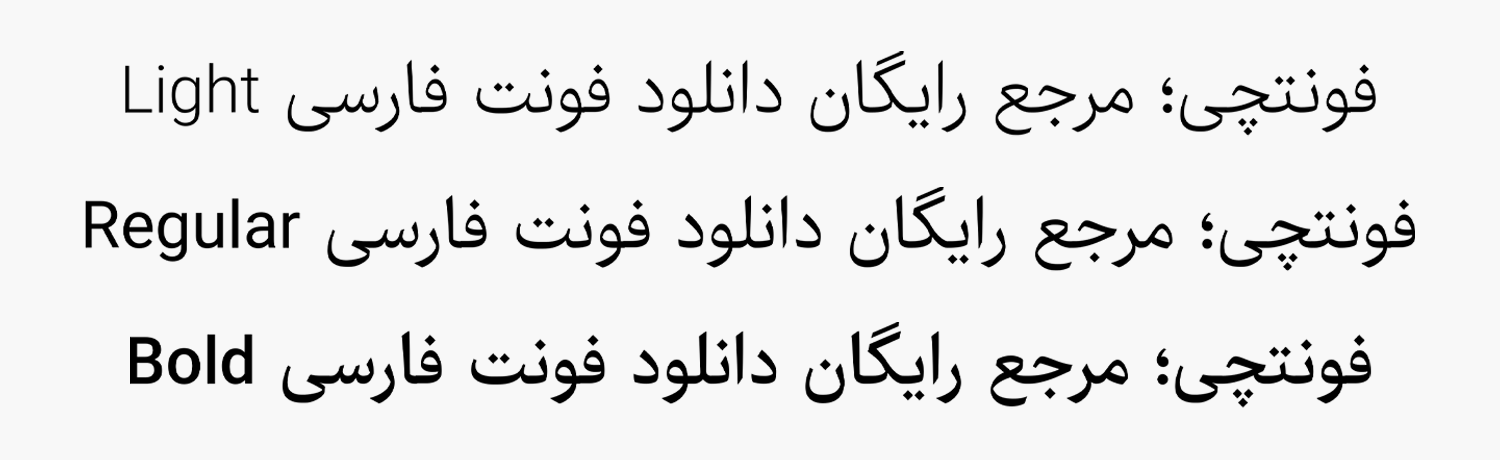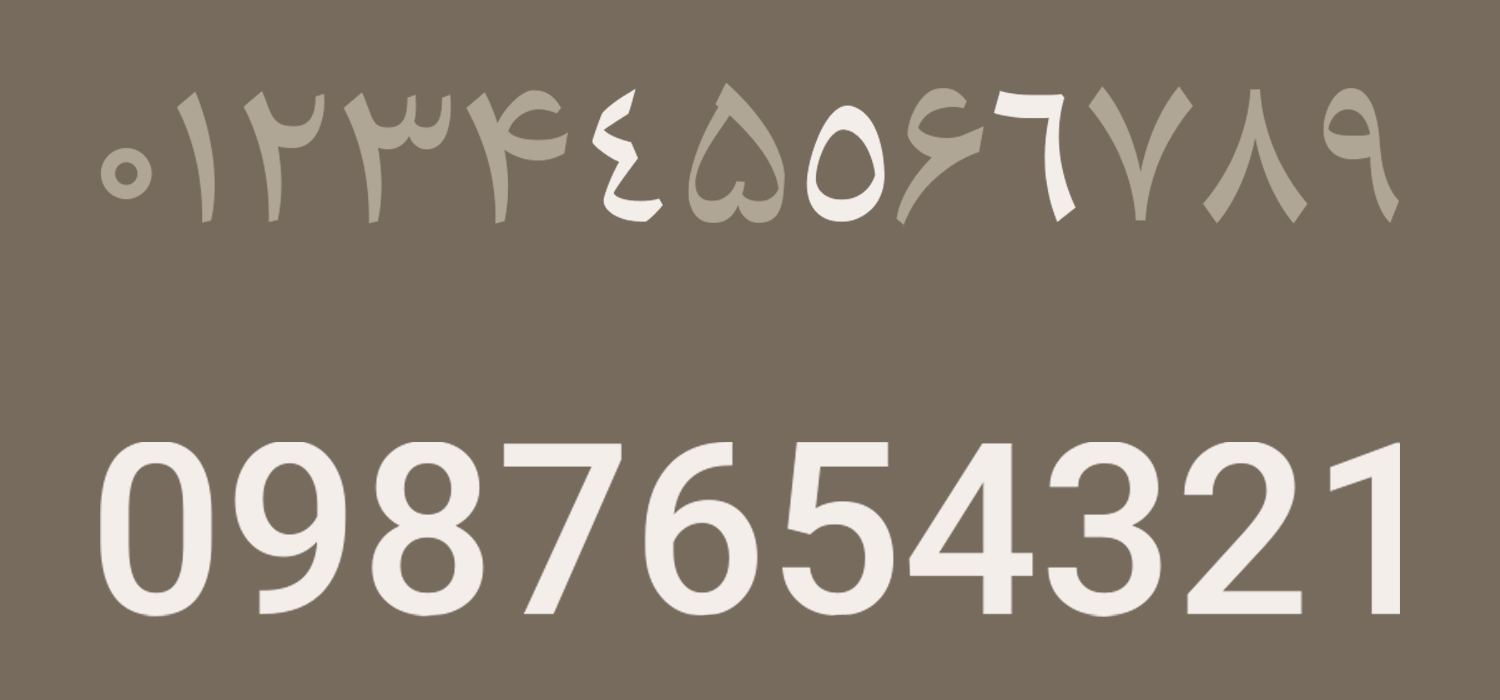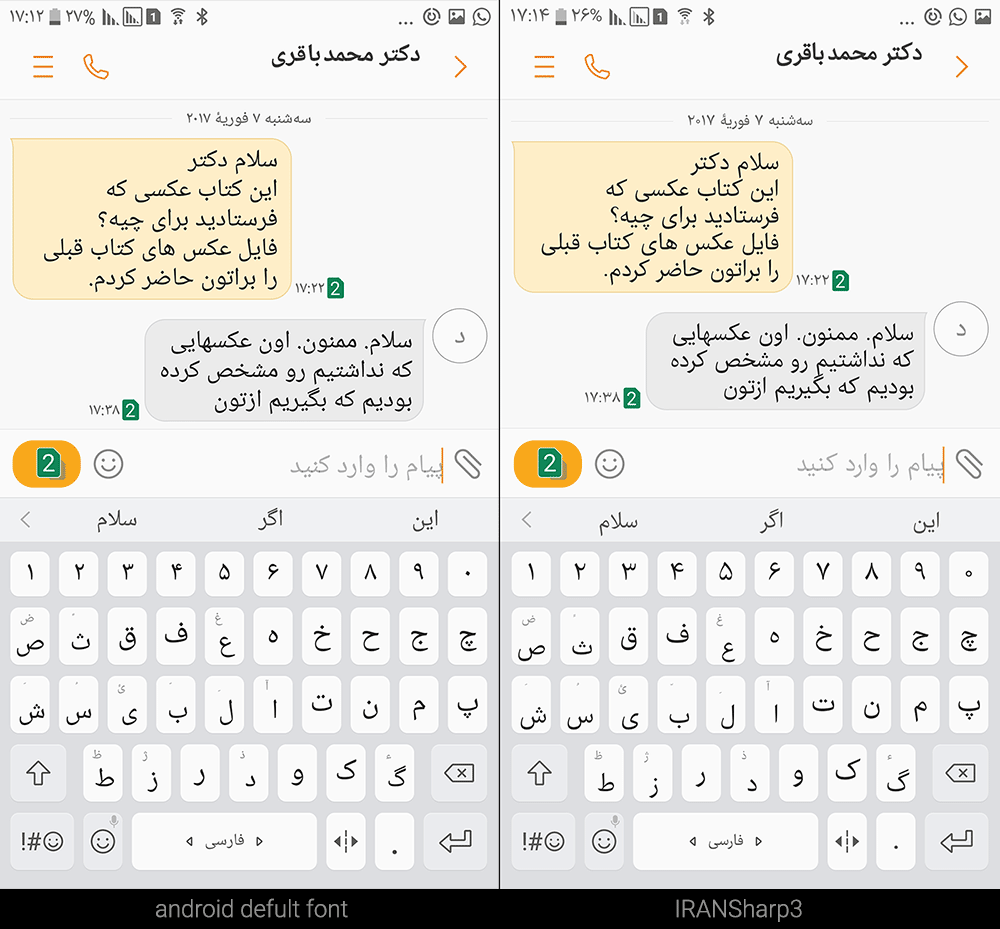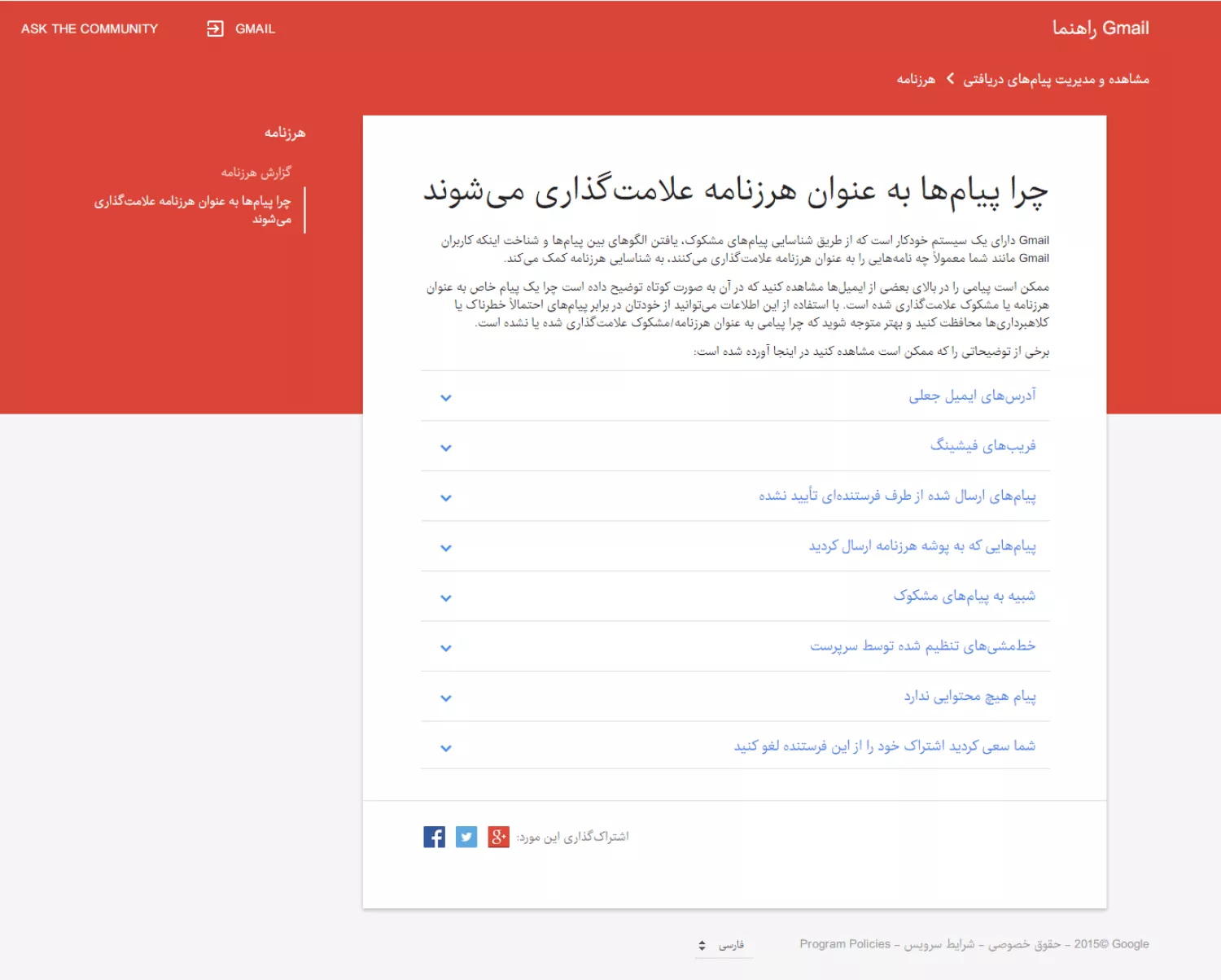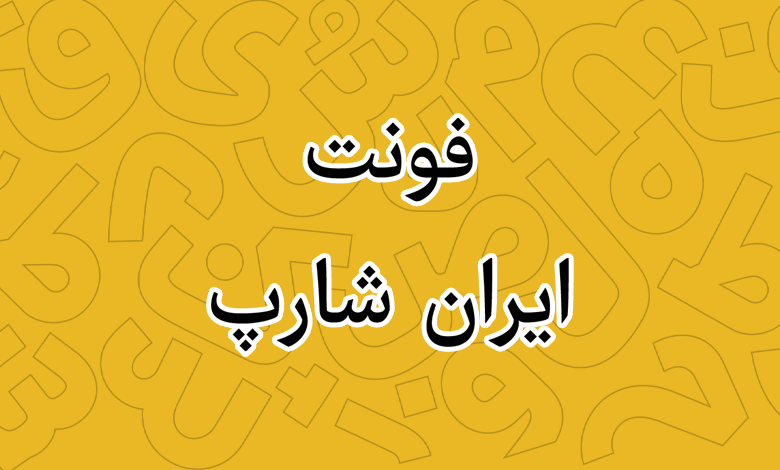
فونت ایران شارپ (iran-sharp)
فونت ایران شارپ (به انگلیسی: iran-sharp) از دیگر قلمهای فارسی مناسب برای متنهای طولانی است که بیشترین کاربرد را در صنعت مطبوعات و چاپ دارد. اما با توجه به اهمیت استفاده از این قلم در چنین صنعتی، برای استفاده در فضای دیجیتال بهویژه وبسایت و اپلیکیشن نیز انتخابی عالی بهشمار میآید.
این قلم که بر اساس خط نسخ طراحی شده، طراحی نزدیکی با بهترین فونت های فارسی معاصر نظیر زر، نازنین، میترا، لوتوس و بدر دارد که توسط مسلم ابراهیمی طراحی شده است. این قلم را میتوان نسخه اولیه برای قلمی در نظر گرفت که در نهایت پس از سالها نسخه پخته شده آن با نام فونت فرهنگ توسط همین طراح ساخته و در دسترس عموم قرار گرفت.
در ادامه این نوشته از سایت فونتچی به نقد و بررسی کامل قلم ایران شارپ خواهیم پرداخت؛ فونتی در قالب سه وزن که در ۵ فرمت فایل مختلف در دسترس بوده و با توجه به تنوع و ساختاری که از نظر نسخه مناسب برای اعداد فارسی و بدون حروف انگلیسی دارد، میتوان از آن برای متنهای بلند بهترین بهره را برد.
با اینکه قلمهایی نظیر زر، میترا، نازنین و… بیش از نیم قرن است که مورد استفاده قرار میگیرند؛ اما با ظهور سبک دیجیتال و فاصله گرفتن دنیای آن از حروفچینی، اکنون مشکلات و ایرادهای مختلفی را داشتند که در سالهای گذشته احساس به وجود قلمی در همان سبک کاملا وجود داشت.
با اینکه در این سالها افراد مختلفی سعی داشتند که قلمهای مورد نظر را اصلاح کرده و تغییراتی در آن ایجاد کنند که متناسب با نیاز فعلی باشد؛ اما این کار به سرانجام نرسید تا اینکه در نهایت قلم ایران شارپ متولد شد.
سبک طراحی و وزن فونت ایران شارپ
استفاده از فونت ایران شارپ برای افرادی که وابستگی زیادی به سبک فونتهای زر، نازنین، میترا، لوتوس و بدر داشتند مناسب است تا قلمی عاری از اشکالات نرمافزاری را در اختیار داشته باشند.
فونت ایران شارپ در طول این سالها بارها بهروزرسانی شده و ضمن رفع ایرادات جزئی که در آن وجود داشته تغییراتی نیز بر روی آن اعمال شده است که در نهایت به شکل امروزی آن را مشاهده میکنید.
این قلم مشابه سایر تایپفیسهای فارسی از سه وزن نازک (Light)، معمولی (Regular) و ضخیم (Bold) پشتیبانی میکند که تمامی بخشهای حروف در هر سه وزن به نسبت تغییراتی وزنی به خود گرفته و هر چه وزن بیشتر میشود، فونت از حالت استخوانی خارج شده و ظاهری نرم و شارپتر بهخود میگیرد.
پشتیبانی از زبان فارسی و عربی
اگر به دنبال بهترین فونت فارسی هستید، ایران شارپ را میتوان یکی از این قلمها دستهبندی کرد؛ با اینکه شاید این قلم را زیاد در فضای دیجیتال ندیده باشید، اما در فضای مطبوعات و صنعت چاپ همچون روزنامه و کتابها بهوفور از این قلم استفاده میشود.
این قلم علاوه بر زبان فارسی، از زبان عربی نیز پشتیبانی میکند. این زبان به لطف اینکه بر پایه رسم خط فارسی است در این قلم قرار داده شده است که علاوه بر پشتیبانی از حروف و گلیفهای استاندارد فارسی، از حروف عربی نیز پشتیبانی میکند.
برای نمونه میتوان به حروف «ک، ی، ه، ؤ، ئ» اشاره کرد که در زبان فارسی مورد استفاده قرار نمیگیرند؛ در حالی که زبان عربی مملو از این ساختارها میباشد.
پشتیبانی این فونت از زبان انگلیسی نیز فراهم است، اما با این تفاوت که از فونت پیشفرضی که درون گلیفهای آن جاسازی شده استفاده میشود که طراحی بسیار نزدیکی بر مبنای نسخه فارسی و عربی قلم دارد.
ویژگی دیگر قلم ایران شارپ، پشتیبانی استاندارد حروف در زبان فارسی و عربی است. در این قلم اعداد «۴۵۶» عربی که نسبت به اعداد فارسی «۴۵۶» ظاهر متفاوتی دارند پیاده شده است. کافی است صفحه کلید شما روی زبان عربی قرار داشته باشد تا بتوانید از این اعداد استفاده کنید.
اما علاوه بر این نسخه، در درون بسته دانلود فونت ایران شارپ پوشه مخصوص اعداد فارسی هک شده نیز قرار دارد. این گروه از فایلهای فونت که به اختصار با پیشوند FD که مخفف Farsi Digits است نامگذاری شدهاند، فاقد اعداد لاتین بوده و در عوض وقتی اعداد را بر مبنای زبان انگلیسی یا با استفاده از بخش ماشین حساب صفحه کلید تایپ کنید، فارسی تایپ خواهند شد.
مناسب فونت موبایل و مطبوعات
همانطور که اشاره شد فونت ایران شارپ از نظر خوانایی انتخابی عالی بهشمار میرود؛ چرا که یک فونت کاملا شارپ محسوب میشود که تمامی بخشهای حروف نظیر دندانهها، منحنیها و خطوط قائم به شکلی درنظر گرفته شده که موجب خوانش راحت متنون طولانی میشود.
لذا از این فونت میتوانید به عنوان فونت پیشفرض گوشی موبایل نیز استفاده کنید که در تصویر زیر نمونه نصب شده آن را بر روی گوشی سامسونگ مشاهده میکنید.
از دیگر کاربردهای این قلم میتوان به استفاده در فضای مطبوعات و صنعت چاپ اشاره کرد که بیشتر برای چاپ روزنامه، مجلات، کتاب و حتی طراحی جلد کتب استفاده میشود.
در تصویر بالا نمونه این قلم را برای صفحه راهنمای جیمیل مشاهده میکنید که مربوط به نسخههای قدیمی بوده است. همانطور که میبنید از وزنهای مختلف آن در این صفحه استفاده شده ایت که تمامی متون خوانایی لازم را در دستگاههای مختلف دارند.